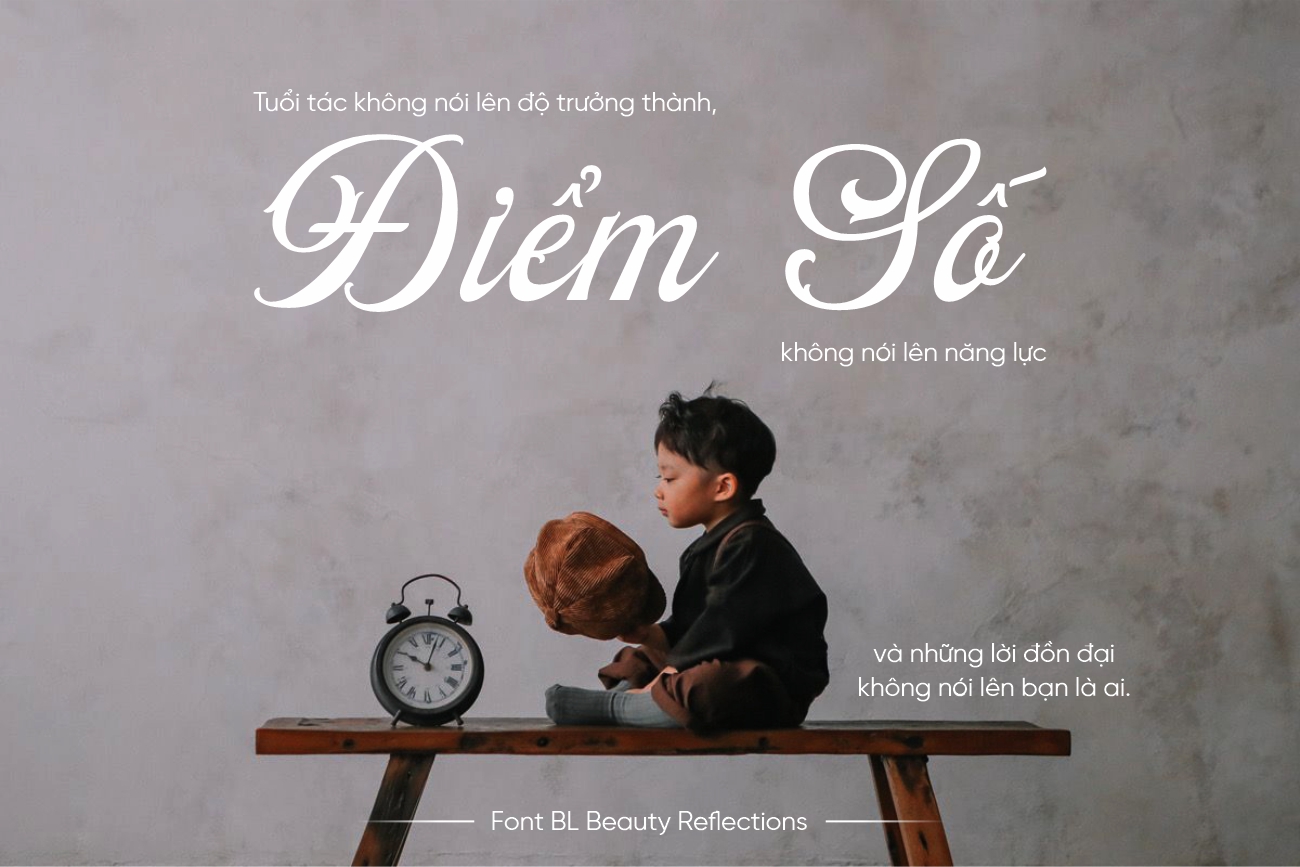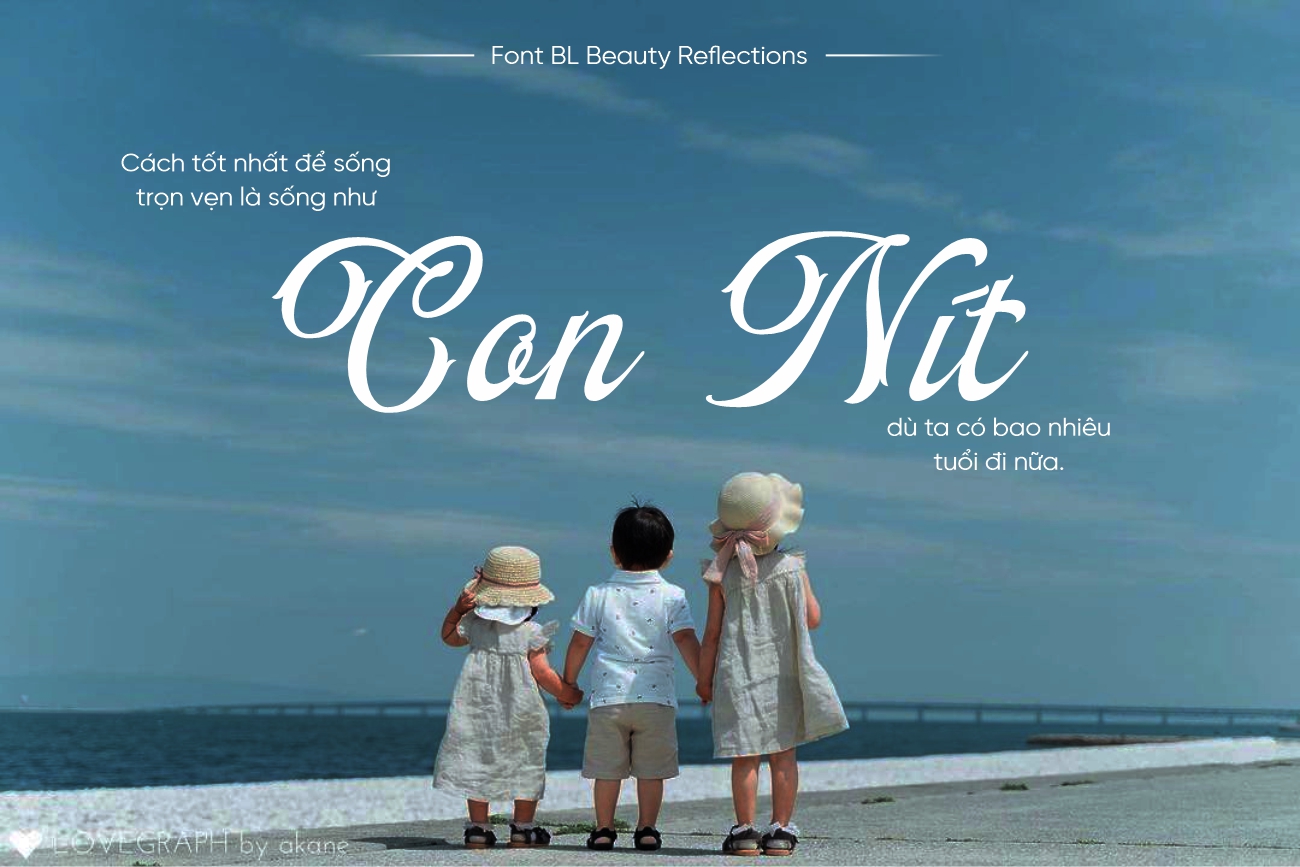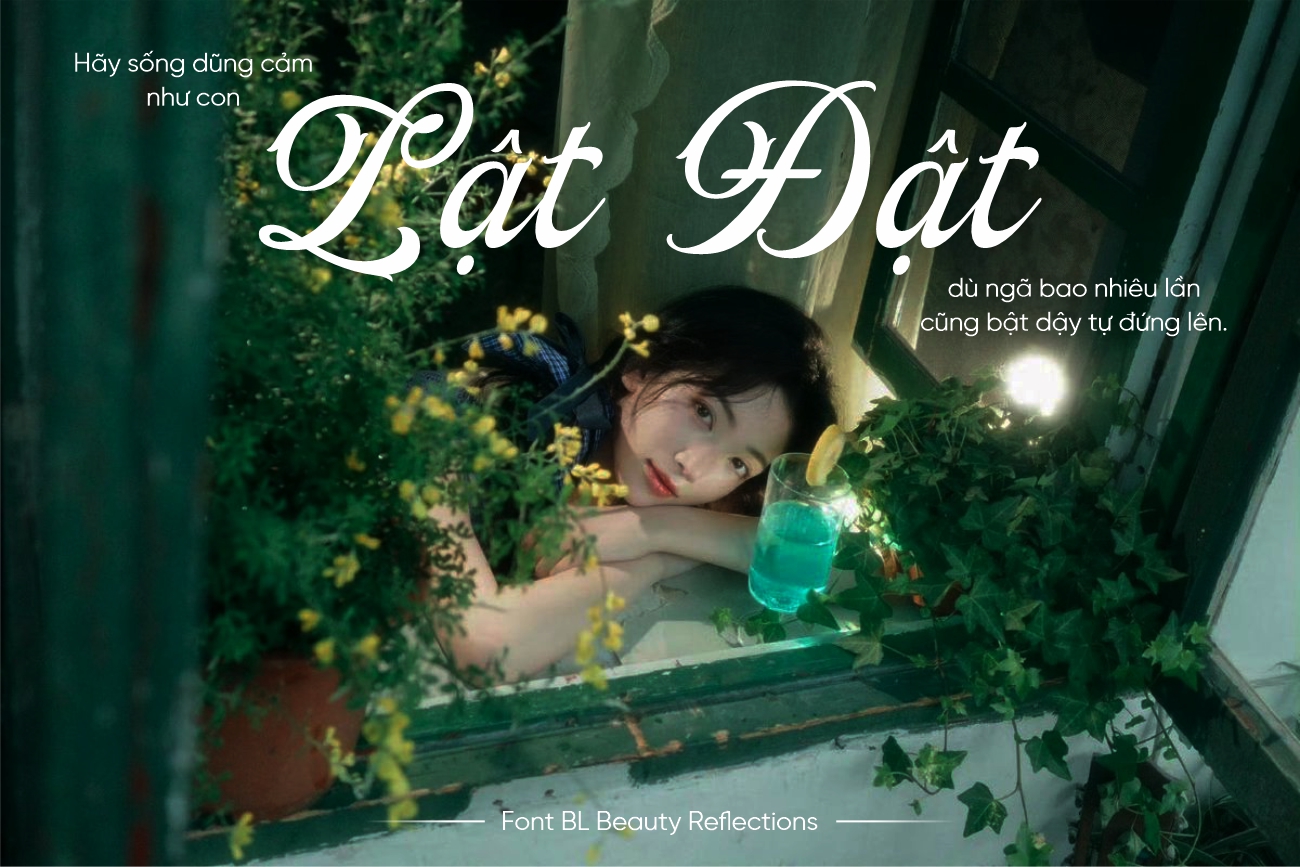
2 font BL Beauty Reflections - Font chữ mềm mại uốn lượn
BL Beauty Reflection là một font chữ mang phong cách chữ viết tay mềm mại và thanh lịch, được thiết kế để tôn lên vẻ đẹp nhẹ nhàng, tinh tế và nữ tính. Với những nét bút uốn lượn tự nhiên, font này mang đến cảm giác như được viết bằng bút lông trên giấy mịn — vừa hiện đại vừa cổ điển.
Đặc điểm nổi bật:
Nét chữ mảnh mai, uyển chuyển và có độ nghiêng nhẹ, tạo cảm giác sang trọng.
Kết hợp hoàn hảo giữa chữ thường và chữ hoa cách điệu, giúp nổi bật trong tiêu đề hoặc logo.
Thiết kế thiệp cưới, logo mỹ phẩm, thương hiệu thời trang, bìa sách, hoặc quote nghệ thuật.
Các dự án cần phong cách nữ tính, lãng mạn, nhẹ nhàng.
Gợi ý: Kết hợp BL Beauty Reflection với font sans-serif mảnh (như Montserrat hoặc Poppins) để tạo điểm nhấn tinh tế và dễ đọc.